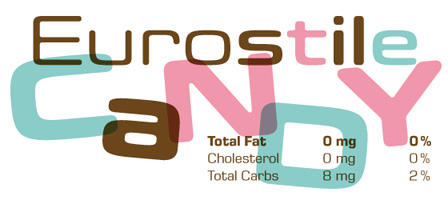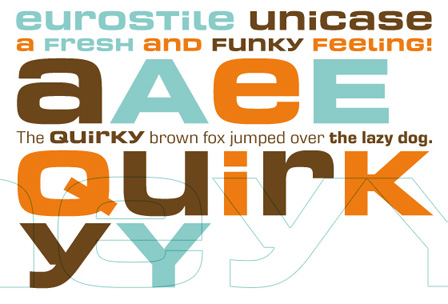
■■■ Eurostileに新たな2書体が登場! ■■■
小林章氏が手がけたEurostile Candy とEurostile Unicaseは、新しいEurostile ファミリーの副産物で、どちらもディスプレイ向けに主眼を置いています。
何とも可愛らしいネーミングのEurostile Candy。コーナーとジョイントが丸く処理されて、よりフレンドリーでソフトなイメージです。a、 s、 t などのストロークは取り除かれ、n、r などではジョイントが単純化されてよりスクエアなシェイプになっています。斬新でクール、ディスプレイにぴったりですね。
Eurostile Unicase ではアセンダーとディセンダーが大胆に処理され、全てのレターが同じハイト(高さ)になっています。aやeも大文字と同じハイト、小文字 y もベースラインとトップハイトに収まるよう上側に位置しています。大文字を使用するのと同様の効果がありますが、よりフレッシュでファンキー、更に強いインパクトを与えるでしょう。
Eurostile Candyには3つのウェイト、Regular、Semi Bold、Bold があり、それぞれEurostile NextのExtended、Extended Semi Bold、Extra Bold と対応しています。
Eurostile Candy Regular
Eurostile Candy Semi Bold ![]() |
Eurostile Candy Bold ![]() |
Eurostile Unicaseのウェイトは1つだけですが、ご覧の通りとってもヘビー、Eurostile Next のBold よりもヘビーです。
Eurostile Unicase Regular
ヘッドラインやタイトルにEurostile Candy やEurostile Unicase、テキストにEurostile Next を使えば素晴らしい組み合わせになるでしょう。
古き良きEurostileの面影を残しつつ、ロゴやコーポレートアイデンティティとしてとっても新鮮です。Eurostile Candy とEurostile Unicase、是非トライ下さい!!
Helvetica forever Story of a Typeface
身近な街角の書体から多くのグローバル企業の指定書体まで、世界市場を席巻し驚くべき広範囲にわたり使用されているこの魅力的な書体を取り上げます。
会場では日本人デザイナーを含む数多くの国のグラフィックデザイナーによってデザインされたポスターや数々のグッズなど、ヘルベチカを使用した様々な時代の作品や資料を展示。その魅力と実績を、ラース・ミュラー社代表のラース・ミュラー、デュッセルドルフ応用技術大学のヴィクトル・マルシー、フィリップ・トイフル、三氏のキュレーションによりご紹介いたします。
また展覧会に合わせ、ラース・ミュラー、ヴィクトル・マルシー両氏による著書『Helvetica forever』の日本語版も刊行の予定です(ビー・エヌ・エヌ新社)。クラシックにして先端、ヘルベチカの世界をぜひお楽しみください。